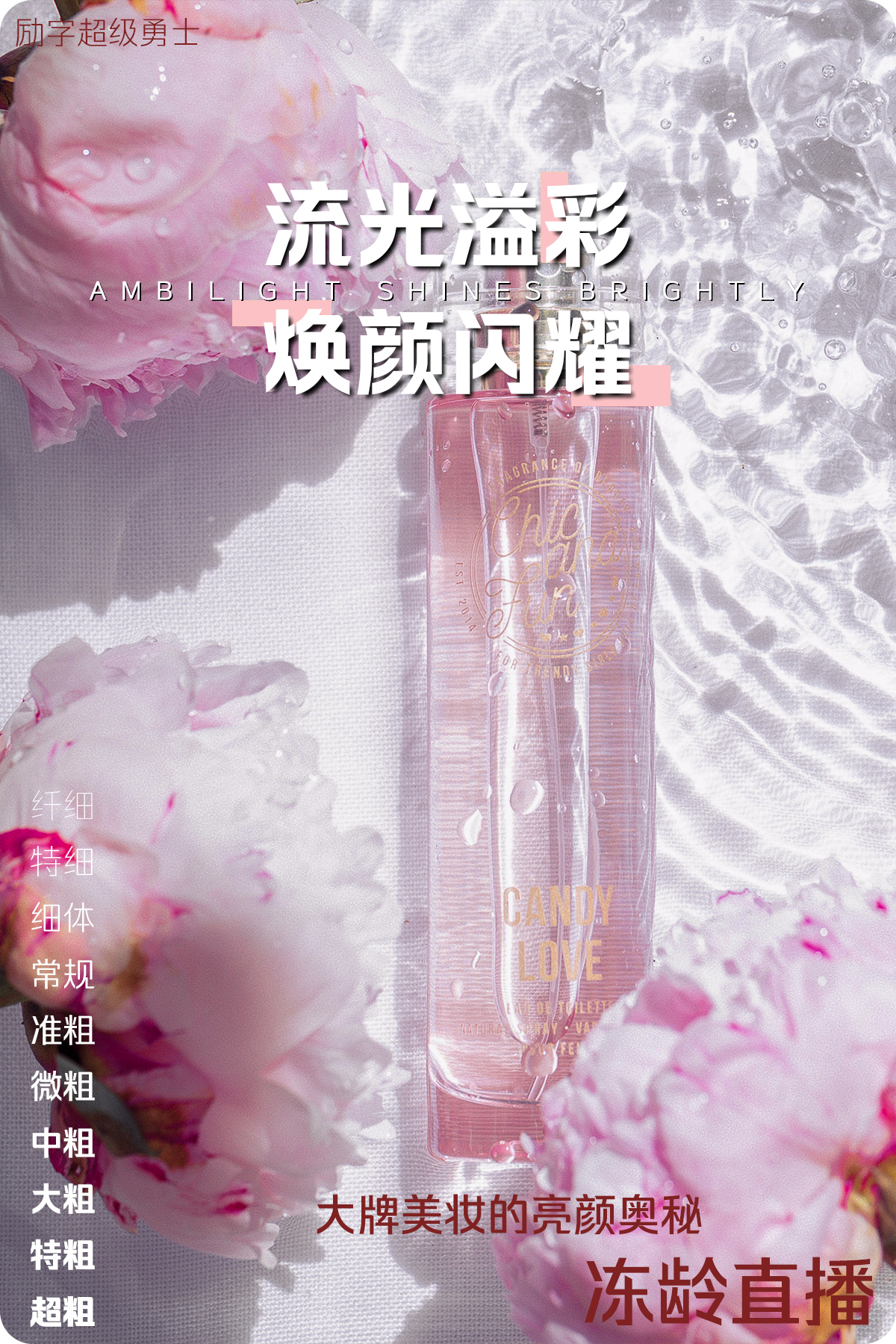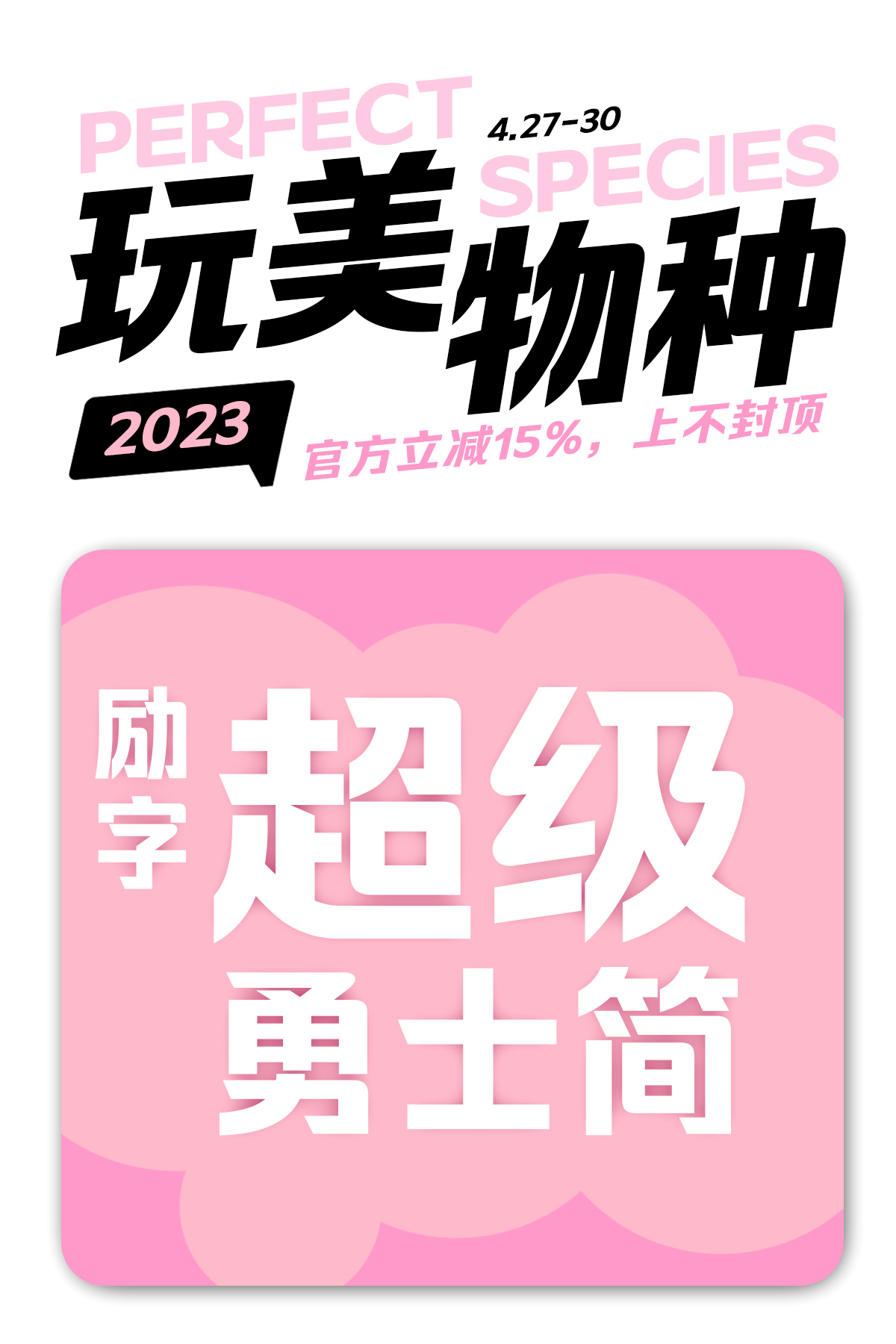
2023年小红书最火爆的美妆字体推荐——励字超级勇士简
时代风暴瞬息而至,现在移动时代的生活经验入口,现在由百度更替为小红书了。小红书作为一个内容型社区,尽管承载着安利种草的作用,但归根结底还是个社区。用户在浏览时更多是抱着休闲消遣,各种好吃好玩好看的花样种草集合地。
对美妆品牌与博主而言,小红书的最新聚光平台与运营机制特别友好。励字造梦局安利1款美妆字体,绝对的吸睛种草效果一绝,快来看看吧~
励字超级勇士简起笔处倾斜和平直设计灵活处理,灵动妆效跃然纸上,
折角笔画由外圆角与方角有序组合,正如美妆叠加时的完美搭配,
撇捺弧度饱满,流畅度、亲肤感满分。